썸네일 폰트 추천, 배경 유형별로 골라야 진짜 읽힌다
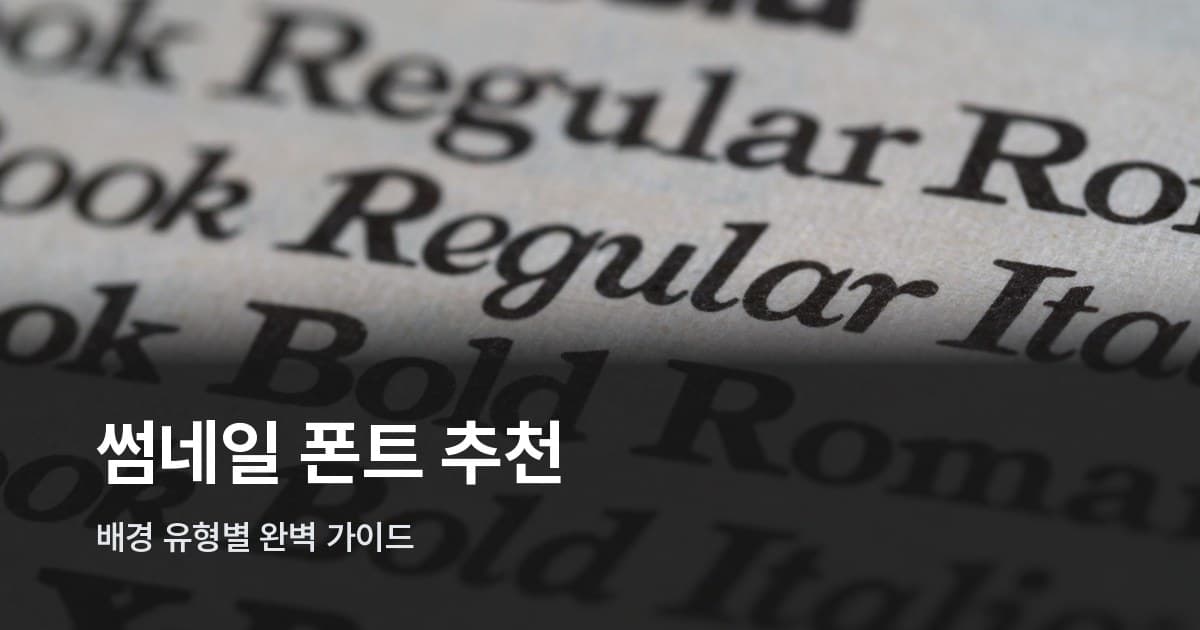
썸네일 만들다가 "이 폰트가 왜 이렇게 안 읽히지?" 싶었던 적 있지 않으세요? 분명히 예쁜 폰트인데 완성하고 나면 뭔가 흐릿하고, 결국 매번 쓰던 폰트로 돌아오는 그 경험요. ㅎㅎ
사실 문제는 폰트 자체가 아니라 배경과의 매칭이에요. 밝은 배경에 잘 먹히는 폰트가 있고, 복잡한 사진 배경에서는 전혀 안 먹히는 폰트가 있거든요. 그런데 기존 썸네일 폰트 추천 글들은 대부분 이름 나열로 끝나버려요. "이 폰트 예뻐요, 이것도 좋아요" — 근데 내 썸네일 배경에 맞는 건 뭔지는 알 수가 없죠.
그래서 이 글에서는 배경 유형(밝음·어두움·복잡)과 폰트 굵기(Weight)를 기준으로, 무료 한글 폰트 8종을 직접 비교표로 정리했어요. 유튜브 썸네일·블로그 대문·릴스 커버 3가지 용도별 추천 조합도 함께 담았으니 한 번만 읽으면 끝납니다.
썸네일 폰트, 이름보다 굵기가 먼저예요
폰트를 고를 때 이름부터 찾는 경우가 많은데, 사실 굵기(Weight) 가 더 중요한 기준이에요.
모바일 피드에서 썸네일은 가로 170px 안팎으로 표시되고, 3초 안에 눈에 안 들어오면 그냥 스크롤됩니다. 이 환경에서는 획이 얇은 폰트가 배경 속에 그냥 묻혀버려요.
폰트 굵기는 Thin(100)부터 Black(900)까지 9단계가 있어요. 썸네일에서 안전하게 쓰려면 ExtraBold(800) 이상이 기준선입니다. Bold(700)도 배경이 단색이고 대비가 확실하면 괜찮지만, 복잡한 사진 배경 위에선 위험해요. Regular나 Medium은 썸네일에 쓰면 거의 보장된 실패예요 ㅋㅋㅋ
두 번째로 볼 건 자간이에요. 자간이 너무 좁으면 소형 화면에서 글자가 뭉개지고, 너무 넓으면 임팩트가 흩어져요. 썸네일용 폰트는 자간이 적당히 열린 구조이거나, 디자인 툴에서 자간을 살짝 좁혀 쓰는 게 좋습니다.
배경 유형별 무료 한글 폰트 비교표
아래 표는 배경을 밝음·어두움·복잡 세 유형으로 나누고, 각각에 맞는 무료 한글 폰트 8종을 정리한 거예요. 모두 상업용 무료(개인·영리 포함) 폰트입니다.
| 폰트명 | 최대 굵기 | 밝은 배경 | 어두운 배경 | 복잡한 배경 | 라이선스 |
|---|---|---|---|---|---|
| 검은고딕 (Black Han Sans) | Black (단일) | ★★★ | ★★★★ | ★★★★★ | OFL (Google Fonts) |
| 에스코어드림 8·9호 | ExtraBold(8)·Black(9) | ★★★★ | ★★★★ | ★★★ | 에스코어 무료배포 |
| 프리텐다드 ExtraBold/Black | Black(900) | ★★★★ | ★★★★ | ★★★ | OFL (GitHub) |
| 어그로체 B | Bold(3단계 중 최상) | ★★★ | ★★★★ | ★★★★ | 샌드박스 무료배포 |
| G마켓산스 Bold | Bold(700) | ★★★★ | ★★★ | ★★ | OFL (G마켓) |
| 나눔스퀘어 ExtraBold | ExtraBold(800) | ★★★★ | ★★★ | ★★ | OFL (네이버) |
| 도현체 | Bold 계열 (단일) | ★★ | ★★★ | ★★ | 배민 무료배포 |
| 한나체 Pro | 단일 굵기 | ★★★ | ★★★ | ★★ | 배민 무료배포 |
★ 많을수록 해당 배경에서 가독성 우수. 별 2개 이하는 그 배경에 비추천.
표를 보면 복잡한 배경에서 가장 강한 건 검은고딕이에요. 단 하나의 굵기인 Black만 존재하는데, 역설적으로 그게 장점이 됩니다. 획이 두꺼워서 풍경 사진이나 그라데이션 배경 위에서도 글자가 절대 안 묻혀요. 반면 G마켓산스나 도현체는 밝고 단순한 배경에서는 예쁜데, 복잡한 배경 위에선 힘을 못 써요.
폰트별로 어울리는 채널 느낌이 따로 있어요 🎨
비교표만 보면 수치로 보이지만, 실제로는 각 폰트마다 "어울리는 분위기"가 달라요.
검은고딕(Black Han Sans)은 솔직히 예쁘다기보다 강하다. 디자이너들이 미적 감각을 잠시 내려놓고 "일단 읽혀야 한다"는 판단이 섰을 때 꺼내는 폰트예요. 그래서 실제 썸네일에서 보면 배경이 복잡한 현장 사진이나 정신없는 합성 이미지 위에서도 글자가 칼같이 살아 있어요. '충격 사실', '진짜 후기', '논란 정리' 같이 읽는 순간 집중하게 만들어야 하는 제목에 잘 어울리고, OFL 라이선스라 상업 사용에 제한도 없습니다.
에스코어드림 8·9호는 꽉 찬 사각형 자형이라 정보 채널이나 지식 채널의 뉴스 스타일 썸네일에 잘 어울려요. 뉴스 앵커 배경이나 깔끔한 슬라이드형 썸네일에 올리면 "정보를 제대로 다루는 채널"처럼 보이는 신뢰감이 생기거든요. Thin부터 Black까지 9단계 굵기가 있어서 한 폰트 패밀리 안에서 헤드라인과 부제를 함께 쓸 수 있다는 것도 장점입니다.
프리텐다드 ExtraBold/Black은 요즘 브이로그·뷰티·라이프스타일 크리에이터들이 가장 많이 선택하는 폰트예요. 애플이나 토스 앱 UI에서 보던 그 정돈된 느낌을 썸네일에 그대로 옮겨올 수 있거든요. 배경에 흰 반투명 레이어 하나만 살짝 깔아도 복잡한 사진 위에서 안정적으로 읽혀요. OFL 라이선스라 사용 범위도 자유롭습니다.
어그로체 B는 설명하기 어렵게 "힙한" 폰트예요. 자모의 높낮이가 불규칙하고 사선 획이 들어가 있어서, 옆에 다른 반듯한 폰트를 놓으면 확 튀어요. 숏폼 특유의 날 것의 에너지, 밈 감성, 역동적인 장면에 올렸을 때 딱 맞는 분위기가 나고요. 어두운 배경이나 색 대비가 강한 배경일수록 진가가 드러납니다.
G마켓산스 Bold는 굵기 상한이 Bold(700)라는 한계가 있지만, 자형이 둥글고 친근해서 파스텔 배경이나 밝은 단색 배경 위에선 가장 따뜻한 느낌을 줘요. 음식·생활·홈스타일 채널처럼 "편안한 채널"을 표방하는 썸네일에 잘 어울립니다.
용도 3가지별 추천 폰트 조합
썸네일 굵기·배경 원칙은 같아도 플랫폼마다 최적 조합이 달라요.
유튜브 썸네일 (16:9)
유튜브 썸네일은 피드에서 작게 보이다가 마우스를 올리면 크게 미리보이는 구조예요. 주 메시지는 3~5단어 이내, 폰트는 굵게가 기본입니다.
- 임팩트형(충격·폭로·리뷰): 검은고딕 단독 사용. 흰색 또는 노란색으로 쓰고 그림자 효과를 가볍게 추가하면 복잡한 배경에서도 잘 읽혀요.
- 정보·지식형: 에스코어드림 9호 주 헤드라인 + 프리텐다드 Bold 부제목 조합. 같은 계열 고딕이라 위화감 없이 계층을 나눌 수 있어요.
- 브이로그·라이프스타일: 프리텐다드 Black 단독. 배경을 단색이나 흐린 배경으로 정리하면 더 깔끔하게 마무리돼요.
블로그 대문 이미지 (네이버·티스토리 등)
블로그 대문에 어그로체 써봤는데 너무 튀더라고요 ㅋㅋㅋ 블로그 썸네일은 유튜브보다 텍스트를 길게 쓰는 경향이 있고, 소제목이나 설명 문구가 함께 들어가는 경우도 많아서 가독성 기반 고딕체가 훨씬 안전합니다. 메인 텍스트는 G마켓산스 Bold 또는 나눔스퀘어 ExtraBold, 포인트 서브 텍스트에 프리텐다드 SemiBold로 굵기 대비를 주는 조합이 무난하게 잘 읽혀요. 배경은 단색이나 저채도로 정리하는 게 유리하고, 사진 배경이 꼭 필요하다면 반투명 박스를 올리고 그 위에 텍스트를 얹는 방식을 써야 합니다.
릴스·쇼츠 커버 (9:16 세로)
세로 커버는 폰트 한 개, 텍스트 세 단어 이내가 원칙이에요. 두 가지 이상 섞으면 좁은 화면에서 바로 산만해집니다.
- 트렌디·엔터테인먼트: 어그로체 B. 글자 색과 배경 대비를 확실하게 주는 게 핵심이에요.
- 정보·팁형: 에스코어드림 8호. 깔끔하고 정돈된 느낌이 정보 콘텐츠와 잘 맞아요.
썸네일 폰트 자가점검 체크리스트
폰트를 골랐으면 적용 전에 이 3가지만 확인해보세요.
- 굵기 ExtraBold(800) 이상인가? Bold(700) 이하면 복잡하거나 어두운 배경에서 묻힐 수 있어요.
- 배경과 텍스트 색 대비가 충분한가? 어두운 배경엔 흰색·노란색, 밝은 배경엔 검정·진한 색이 기본. 비슷한 명도끼리 겹치면 가독성이 급격히 떨어져요.
- 모바일 화면에서 미리 확인했는가? PC에서 만든 썸네일을 스마트폰으로 봤을 때 글자가 읽히는지 최종 확인. 이 단계를 빠뜨리면 모바일 피드에서 글자가 묻히는 결과가 나와요.
이 세 가지만 통과하면 썸네일 폰트 추천에서 큰 실수는 없어요. 거기에 더해서, 채널이나 블로그 메인 폰트 1개·포인트 폰트 1개를 고정해두면 콘텐츠 전체의 일관성이 자연스럽게 생깁니다. 한 번 정해두면 매번 고민할 필요 없이 빠르게 작업할 수 있고요.